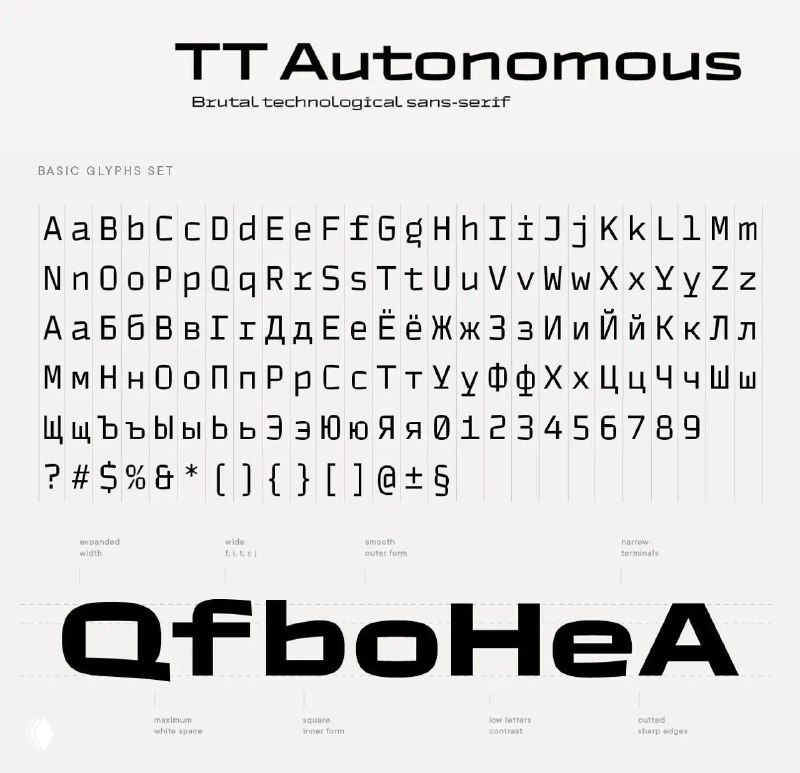
Стильный современный шрифт с оквадраченными скруглениями и технологичным стилем.
Содержит семь вариантов насыщенности, а также курсивные, линейные и вариативные версии. Касса знаков включает стилистические сеты, альтернативы, лигатуры и другие дополнительные знаки. Отлично подойдёт для брендинга, сайтов или мерча.